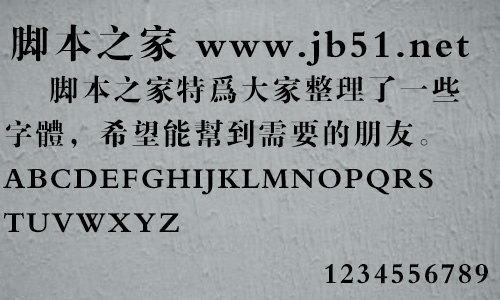
方正大標(biāo)宋繁體字體是方正字體庫中的一種繁體字體,這款字體筆觸粗實(shí),字形大氣,具有很好的視覺感染力,適合應(yīng)用于藝術(shù)設(shè)計(jì)、平面宣傳設(shè)計(jì)、網(wǎng)頁設(shè)計(jì),書法字帖等領(lǐng)域。喜歡的朋友們可以前來下載使用。